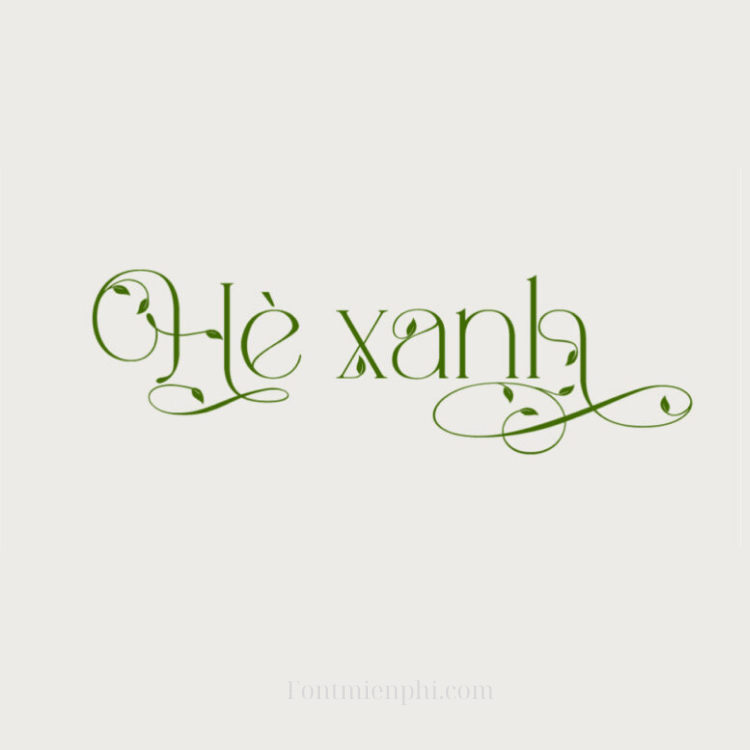
Font Việt hóa Mallong Regular
Tải Ngay Font Việt hóa Mallong Regular – Vẻ Đẹp Hiện Đại Cho Thiết Kế
Giới thiệu về Font Việt hóa Mallong Regular
Trong thế giới đồ họa, việc lựa chọn một bộ Font Miễn Phí chất lượng luôn là ưu tiên hàng đầu của các bạn học sinh và nhà thiết kế trẻ. Font Việt hóa Mallong Regular nổi lên như một lựa chọn hoàn hảo nhờ sự kết hợp tinh tế giữa phong cách Serif truyền thống và những đường nét bo tròn hiện đại. Bộ font này không chỉ mang lại cảm giác thanh lịch mà còn đảm bảo tính dễ đọc tuyệt vời trên cả thiết bị di động và bản in, giúp các dự án học tập trở nên chuyên nghiệp hơn bao giờ hết.
Đặc điểm nổi bật của Mallong Regular
Đặc trưng lớn nhất của Font Việt hóa Mallong Regular chính là cấu trúc hình học cân đối và các chi tiết uốn lượn mềm mại. Phiên bản Việt hóa đã được tối ưu kỹ lưỡng các dấu câu tiếng Việt, giúp người dùng không còn gặp lỗi hiển thị khi soạn thảo văn bản. Nhờ sự chỉn chu trong từng nét chữ, font chữ này cực kỳ phù hợp cho các tiêu đề lớn, bìa sách hoặc thiết kế logo thương hiệu cá nhân, tạo nên dấu ấn riêng biệt và đầy sáng tạo.
Ứng dụng Font Việt hóa Mallong Regular trong giáo dục và thiết kế
Đối với môi trường học đường, Font Việt hóa Mallong Regular là công cụ đắc lực để trang trí báo tường, làm slide thuyết trình hay thiết kế thiệp mời.
Tại sao nên chọn Mallong cho dự án của bạn?
• Độ tương phản vừa phải giúp mắt không bị mỏi khi đọc văn bản dài.
• Phù hợp với nhiều phong cách từ cổ điển đến tối giản.
Việc sử dụng bộ font này sẽ giúp nội dung của bạn trở nên sinh động và lôi cuốn hơn đối với người xem.